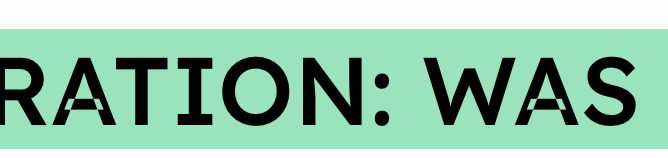
„A“ der Schrift Lexend wird im Web auf iMacs anders dargestellt
Das „A“ der Schrift Lexend wird im Web auf den von mir und dem Kunden für die Verifizierung genutzten iMacs anders dargestellt. Auf iPad und iPhone und allen anderen bisher getesteten Browsern- und Betriebssystemkombinationen ist alles ok.
Ist jemandem das Problem bekannt?
Konnte bisher nichts in Suchmaschinen dazu finden.
Eingebunden wird die lokal auf dem Server abgelegte Schriftart in CSS folgendermaßen:
Habe soeben über GitHub bei den Schriftenentwicklern um eine Korrektur gebeten.
Das scheint eine beliebte Abkürzung bei der Fontgestaltung zu sein:jost.png.1b44a23fe6ae74dd8d04d0bc8d0c756a.png
(Wahrscheinlich dauert’s nicht mehr lange und der bug wird ein feature …)
P.S.: Das ist übrigens die Jost.
🙂 Wenn "alte" Postscript-Logik auf 2022-Screen prallt ...
Ich sehe übrigens den Fehler in der Lexend und Jost (jeweils über Google-Fonts-Vorschau) in Firefox, Safari und Chrome unter macOS 12.1 Monterrey (aktuellst) nicht, da ist alles gut.
Offenbar gab es irgendwo auf Systemebene auch eine Rasterer-Umstellung, die verkehrte Pfadrichtungen anders handhabt (Addition statt Subtraktion bei Teilüberlappung? für die Komplettüberlappung bei Punzen darf das ja nicht einfach verändert werden.)
Da seh ich die Fehler auch nicht, nur auf den Websites, wo sie eingebunden werden.